Thật kỳ lạ, một font chữ có thể khơi dậy đủ hỉ, nộ, ái, ố từ một con người.
Lần đầu tiên được sử dụng vào năm 1931 trong tờ báo The Times của nước Anh, “đại gia tộc” font chữ Times được dùng để thay thế font chữ tiền nhiệm đã lỗi thời, và dần phổ biến khắp thế giới. Danh xưng những đứa con danh tiếng nhất của đại gia tộc này phải kể đến Times, hay Times New Roman.
Font chữ này cũng đã có mặt trên mọi bản Windows từ phiên bản 3.1, và từng được dùng làm font chữ mặc định trên nhiều ứng dụng bao gồm Microsoft Word. Nó được chấp nhận rộng rãi trong lớp học các cấp, trong văn phòng lớn nhỏ, và đã trở thành font chữ chính thức của mọi văn bản ngoại giao của chính phủ Hoa Kỳ vào năm 2004.
Tuy nhiên, thời thế đổi thay, không vị vua nào trị vì mãi mãi.
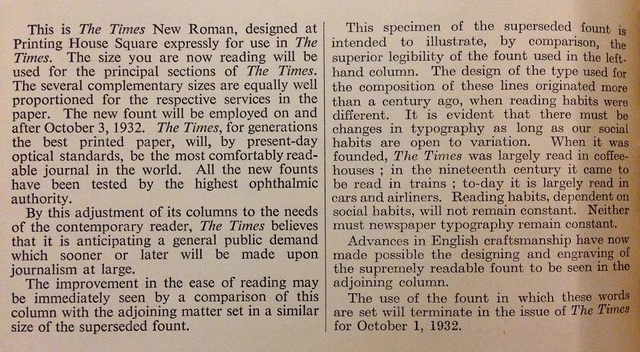
Font Times New Roman (bên phải) so với font chữ lỗi thời (bên trái). Bạn có thể thấy font mới to hơn trên mặt giấy, và có khoảng cách ký tự thoáng hơn - Ảnh: New York Public Library.
Times New Roman thoái vị
Đầu năm 2023, Bộ Ngoại giao Hoa Kỳ đưa ra thông báo chính thức: thay thế Times New Roman, bắt đầu sử dụng font Calibri cho tất cả các văn kiện. Theo tài liệu lưu hành nội bộ, sự thay đổi nhắm tới mục đích hỗ trợ nhân viên dễ dàng đọc chữ trên màn hình.
Tuy nhiên, công cuộc cải cách vấp phải nhiều ý kiến trái chiều. Nhân sự các cấp chính phủ Mỹ đã quá quen với Times New Roman, họ tỏ ra bất bình với quyết định mới. Nhiều người còn bông đùa rằng đây là sự “báng bổ”, và rằng sớm muộn sẽ có người đứng lên đòi lại quyền sử dụng Times New Roman.
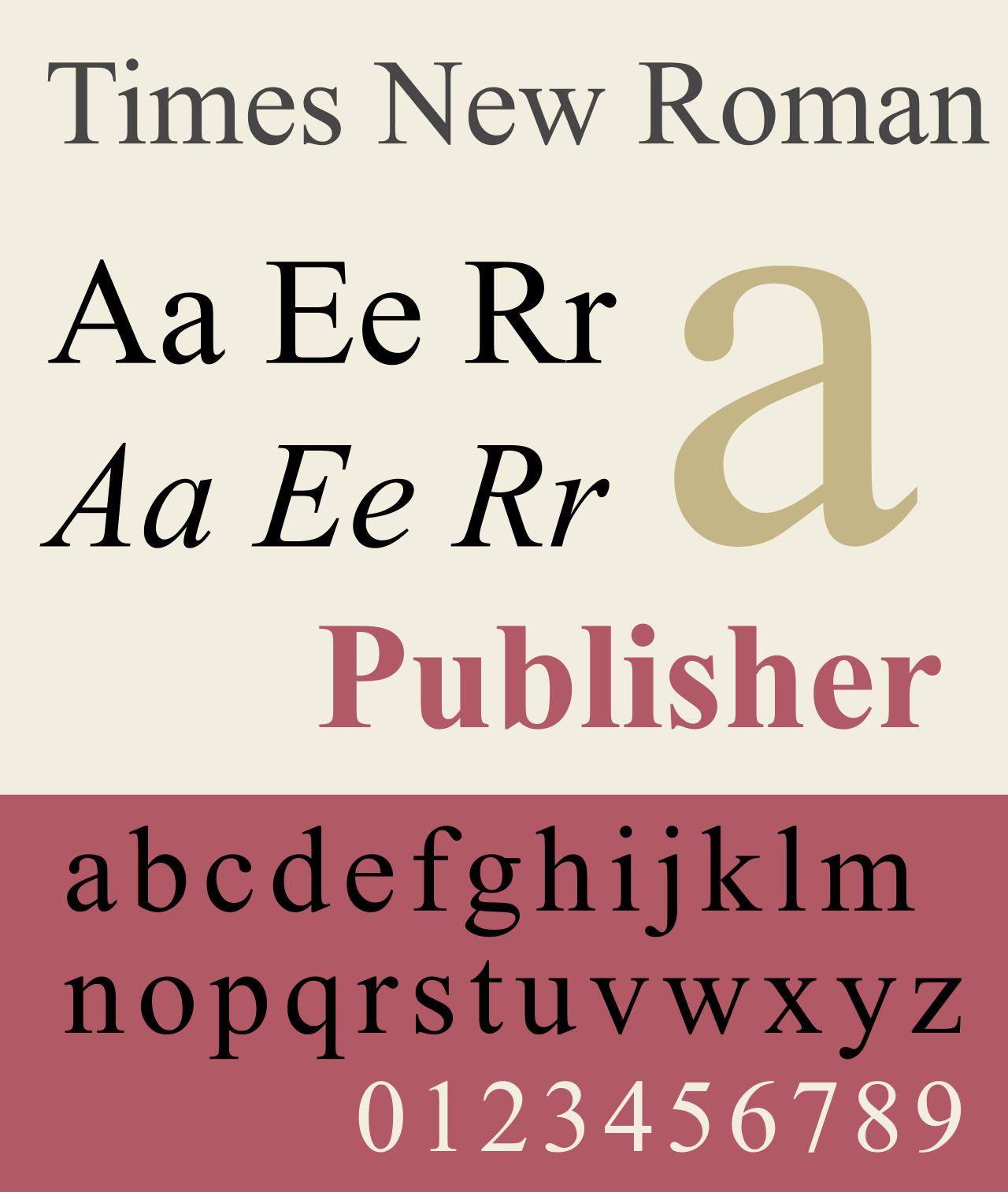
Font Times New Roman được sử dụng trong hiển thị tỉ số một trận đấu diễn ra trong khuôn khổ Euro 2024 - Ảnh: Internet.
Thực tế thì font chữ Calibri không khơi mào được cuộc nổi loạn nào, và màn thay đổi từ Times New Roman sang Calibri có lý lẽ riêng của nó. Những năm gần đây, những nét tinh tế năm xưa của font Times New Roman, là “cánh chữ” và “chân chữ”, bị các cộng đồng thiết kế chê bai. Họ cho rằng vẻ ngoài của Times New Roman không còn phù hợp với bối cảnh hiện đại. Đây cũng là lý do một số nhãn hiệu đã thay thế font dùng trong logo của mình, họ bỏ Times New Roman để sử dụng những font như Helvetica, vốn có vẻ ngoài gọn gàng hơn.
Tuy nhiên, khả năng dễ dọc mới là lý do chính để Bộ Ngoại giao Hoa Kỳ dùng Calibri thay Times New Roman. Trong thời đại mới, khi các ký tự được hiển thị phần nhiều trên màn hình, khả năng dễ đọc của font chữ được đặt lên hàng đầu. Đôi lúc, những nét tô vẽ hoa mỹ của Times New Roman xưa cũ sẽ hiện ra một cách rối rắm trên màn hình, làm khó một số lượng không nhỏ người dùng thiết bị điện tử.
Font Times New Roman nổi tiếng với "chân" và "cánh" - Ảnh: Internet.
Nhưng cớ gì mà đem lòng ghét font chữ?
Bạn có thể tráo “Times New Roman” với bất cứ font chữ nào khác và vẫn có thể tìm được một cộng đồng ghét nó tới say mê. Thực tế, trên những trang sử ghi lại tâm tính người đam mê typography (hay gọi nôm na là những người đam mê font chữ), thì người ta thấy danh sách những font chữ bị ghét dài vô kể.
Trong thời đại Internet kết nối con người một cách xuyên suốt, những người ghét bỏ những font chữ nhất định tìm được những người bạn chung “sở ghét”, rồi họ thành lập cộng đồng để xướng lên tiếng nói chung. Trên mạng, tồn tại những cộng đồng đòi bài trừ Papyrus, những tập thể người căm thù font Comic Sans, hay những nhóm ghét cay ghét đắng font chữ “cơ bản” Arial.
Meme "doge" nổi tiếng sử dụng font Comic Sans - Ảnh: Internet.
Mỗi cộng đồng đều có lý ro riêng cho “sở ghét” của mình. Nhưng theo phân tích của Allan Haley, giám đốc mảng Từ và Chữ cái thuộc công ty Monotype Imaging, một chuyên gia về mọi thứ liên quan tới thiết kế kiểu chữ, thì có 4 lý do khiến một font chữ bị ghét. Chúng là:
1. Thiết kế font chữ bị lạm dụng quá đà
2. Font chữ là bản sao của một font chữ khác
3. Chất lượng font chữ kém
4. Chỉ đơn giản là … quá đáng ghét
Trong bài đăng trên tạp chí Commarts, chuyên gia Haley đi sâu vào từng khía cạnh của 4 lý do trên.
1. Font bị tận dụng đến ngưỡng … lạm dụng
Có lẽ Comic Sans trứ danh đứng đầu bảng xếp hạng những font chữ bị dùng quá đà. Trong những buổi đầu Comic Sans hiện hữu bên trong ứng dụng Microsoft 3D Movie Maker, hay khi nó trở thành một phần trong gói Microsoft Plus! của Windows 95, người ta không căm thù nó như bây giờ.
Nhưng đến khi nó xuất hiện quá đà trên Microsoft Publisher và Internet Explorer, nó bắt đầu thu hút những ánh nhìn khó tính từ cộng đồng. Dễ dàng tiếp cận, ai cũng có thể dùng, Comic Sans xuất hiện liên tục trên các nền tảng Internet, đến mức người ta bắt đầu quen đến mức chán ghét sự hiện diện của nó.
Đôi khi, người ta yêu/ghét một font chữ chỉ vì nó đáng yêu/đáng ghét.